El año se acaba y vamos a ir haciendo resumen de lo que ha dado el año en varios aspectos. El primero y del que vamos a hablar aquí hoy son las 25 mejores tipografías del 2023. Tipografías variadas, con carácter y personalidad que además os vais a poder descargar de forma gratuita.
Tanto si estáis buscando una tipografía interesante para usar en una identidad corporativa como si lo que estáis buscando es una tipografía con personalidad para algún proyecto de diseño gráfico, aquí os vais a encontrar con una selección muy variada. Espero que podáis disfrutar la lista de las mejores tipografías del 2023.
Listado de las mejores tipografías del 2023
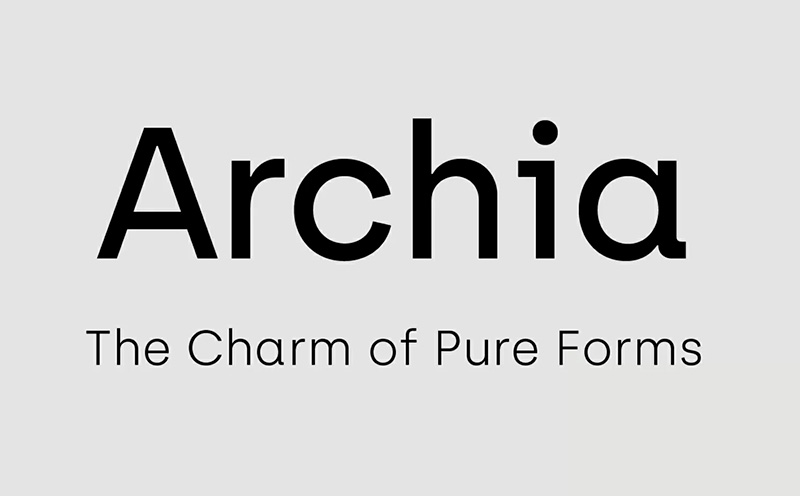
Archia
«Archia» fue diseñada por un diseñador de Gijón, España. Archia es una tipografía sans serif basada en formas geométricas y en un enfoque «tecnológico». La verdad que tiene un punto muy chulo sobre todo en grosores superiores.
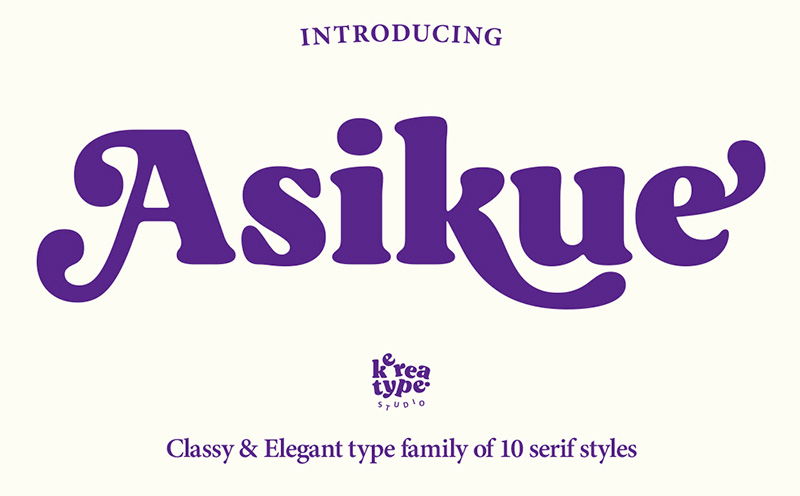
Asikue
«Asikue» es una familia de fuentes serif suave que consta de 10 estilos. La verdad es que a mi me recuerda a la fuente Cooper con su aire retro y ese grosor que la hace tan visual. Yo la recomendaría para tenerla como base para logotipos y para títulos de carteles. Es una de las que más me gusta y creo que es de las mejores tipografías del 2023.
Badrick
«Badrick» es una fuente sans serif condensada imponente con tres pesos que se pueden utilizar para aplicar en una gran variedad de trabajos relacionados con el diseño gráfico. A mi la verdad es que me parece muy elegante y creo que funcionaría muy bien para logotipos relacionados con la hostelería, por poner un ejemplo. Sería una buena base para llevar a cabo un buen diseño de logotipos para restaurantes.
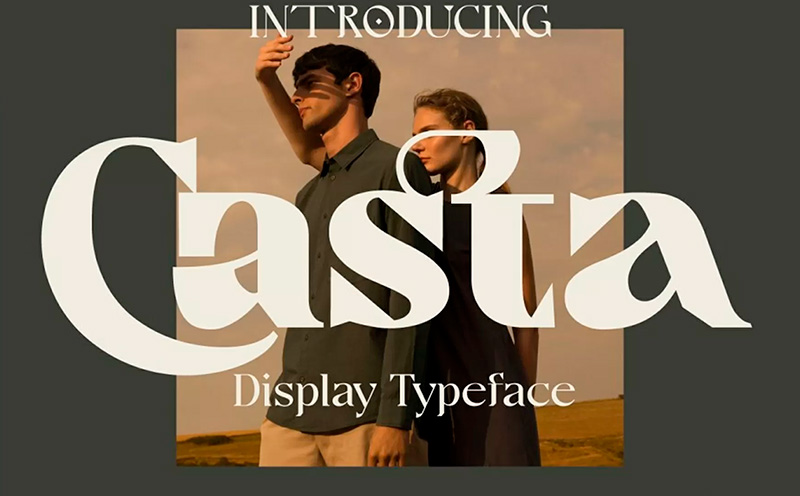
Casta
«Casta» es una nueva fuente serif fresca y moderna con un estilo fuerte y una línea base dinámica. Es tan hermosa en invitaciones como tarjetas de felicitación, materiales de branding, tarjetas de presentación, citas, pósters y mucho más.
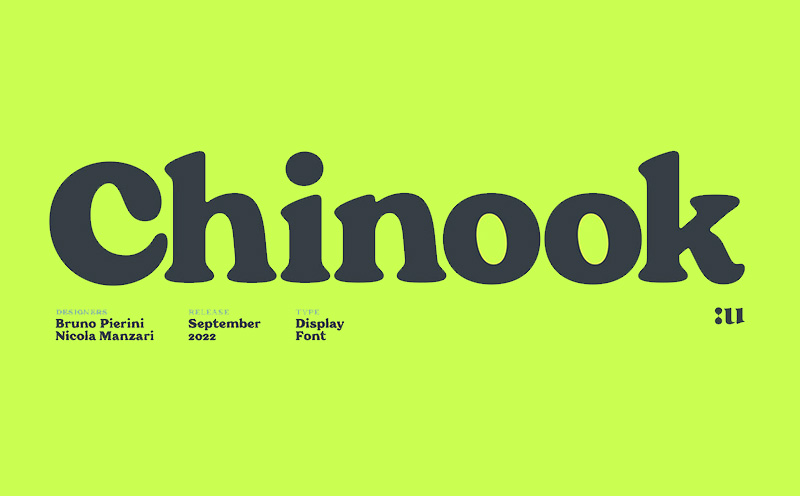
Chinook
«Chinook» es un homenaje a los titulares llamativos icónicos de las películas italianas de la década de 1970. Su aspecto vintage y pesado hace que los titulares, el branding y los logotipos sean cautivadores. Me mola tanto como la que hemos comentado más arriba, Asikue.
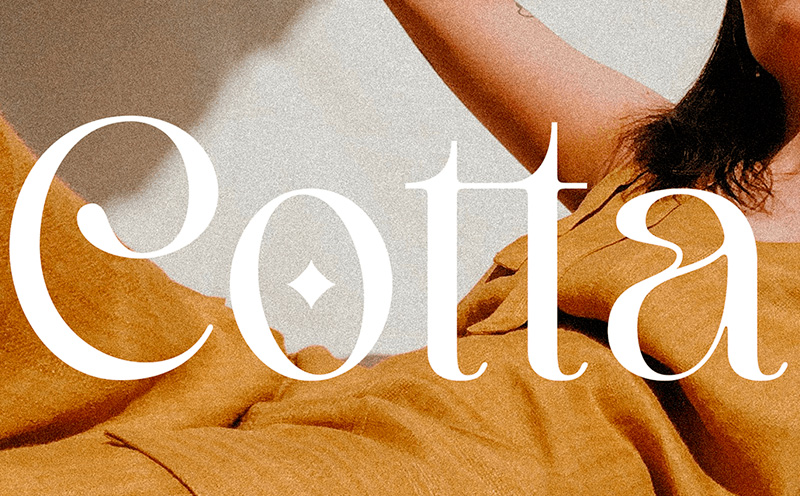
Cotta
«Cotta» es una fuente serif con un carácter ornamental y elegante que fluye con gracia. Yo la veo ideal para invitaciones, carteles de exposiciones y trabajos de diseño gráfico que tengan una aplicación similar.
Creme Espana
«Creme España» es una elegante caligrafía moderna con un toque romántico. Esta fuente es ideal para la decoración de bodas, logotipos, branding y diseño editorial.
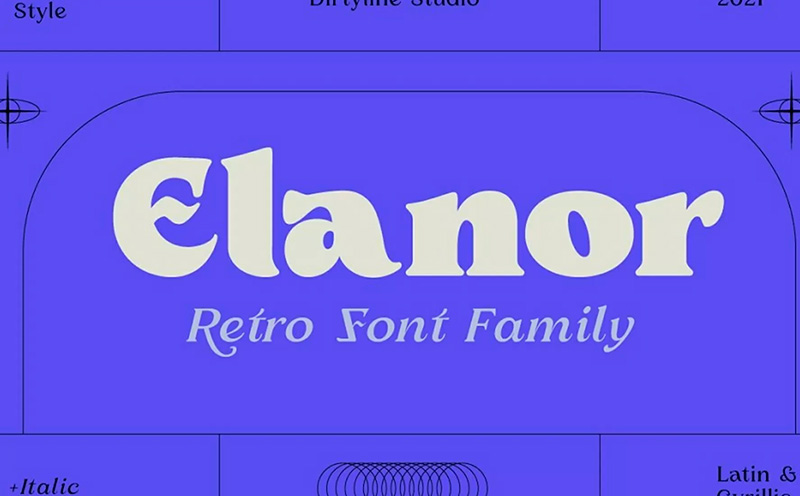
Elanor
«Elanor» es una nueva fuente serif fresca y moderna con un estilo retro, mezclado con toques experimentales. Es tan hermosa en invitaciones como tarjetas de felicitación, materiales de branding, tarjetas de presentación, citas, pósters y mucho más.
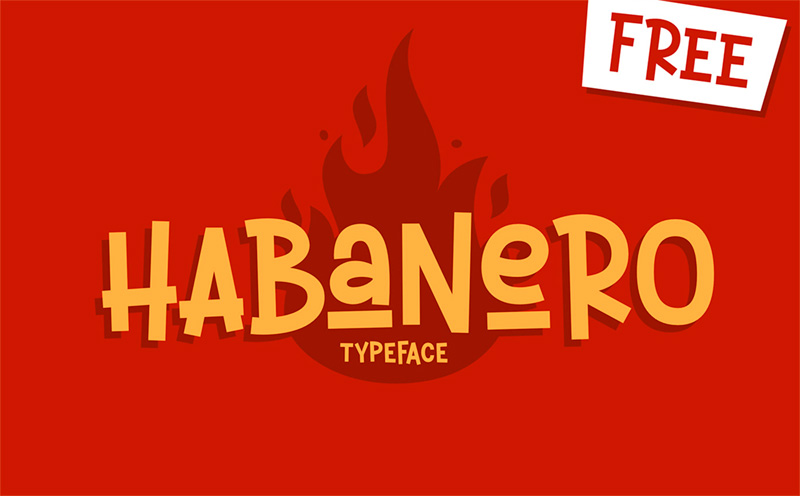
Habanero
«Habanero» es una fuente de exhibición fresca, juguetona y dramática que realzará cualquier diseño. Adecuada para titulares, logotipos y branding, su estilo es limpio y audaz. La verdad es que es de las que me molan de esta lista por su fuerte personalidad. Yo la considero una de las mejores tipografías del 2023 pero también reconozco que no es fácil su aplicación.
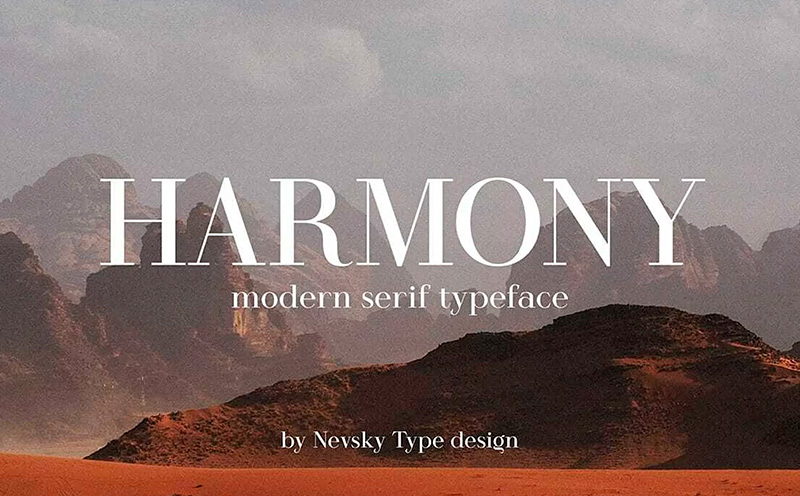
Harmony
«HARMONY» es una nueva fuente serif moderna de Artem Nevsky que aportará un toque de elegancia a cualquier proyecto. Perfecta para invitaciones, tarjetas postales, pósters, portadas de libros, anuncios, sitios web, encabezados de sitios web, logotipos, revistas, etc.
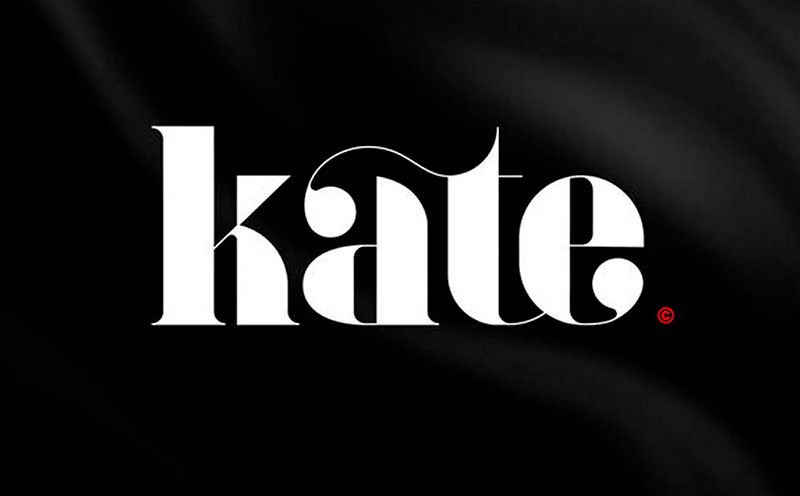
Kate
Creada por Jérémie Gauthier, «Kate» es una fuente serif con 3 pesos de fuente (Display, Medium, Bold) que incluye muchas ligaduras y variaciones. Esta fuente multilingüe es de las mejores tipografías del 2023 para branding, pósters, revistas, packaging y mucho más.
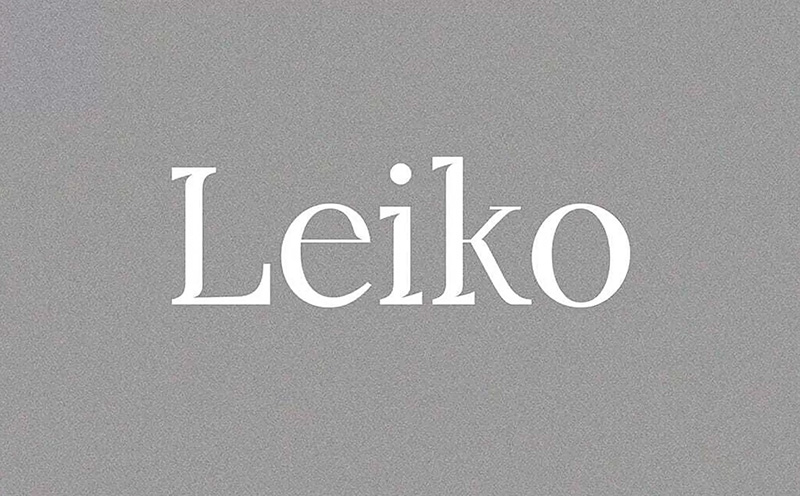
Leiko
«Leiko» es una versátil fuente serif con un contraste moderado, curvas suaves y remates afilados. Leiko es ideal para diseños de branding elegantes y editoriales.
Luthon Southand
«Luthon Southand» es un espectacular dúo de fuentes que incluye una elegante serif y una escritura monoespaciada. Perfecto para envases, branding, revistas, redes sociales y mucho más.
Maghfirea
«Maghfirea» es una fuente serif moderna y elegante. Maghfirea es la elección perfecta para aquellos que desean crear diseños limpios, modernos y minimalistas.
Magilio
Fuentes hermosas y suaves en un estilo contemporáneo que pueden hacer que tus proyectos de diseño luzcan modernos, elegantes y lujosos. Creadas con muchos caracteres alternativos para facilitarte la realización de diversos proyectos de diseño y para que disfrutes mientras escribes.
Tropikal
La tipografía Tropikal es una fusión entre lo vintage y lo moderno, creada con elegancia y aventura en mente. Surgió de la curiosidad por saber cómo se vería una tipografía filipina antigua en el contexto moderno de hoy en día. Tropikal es una reinterpretación moderna de una tipografía con remates inspirada en los billetes bancarios, periódicos y diseños de envases filipinos del siglo XIX.